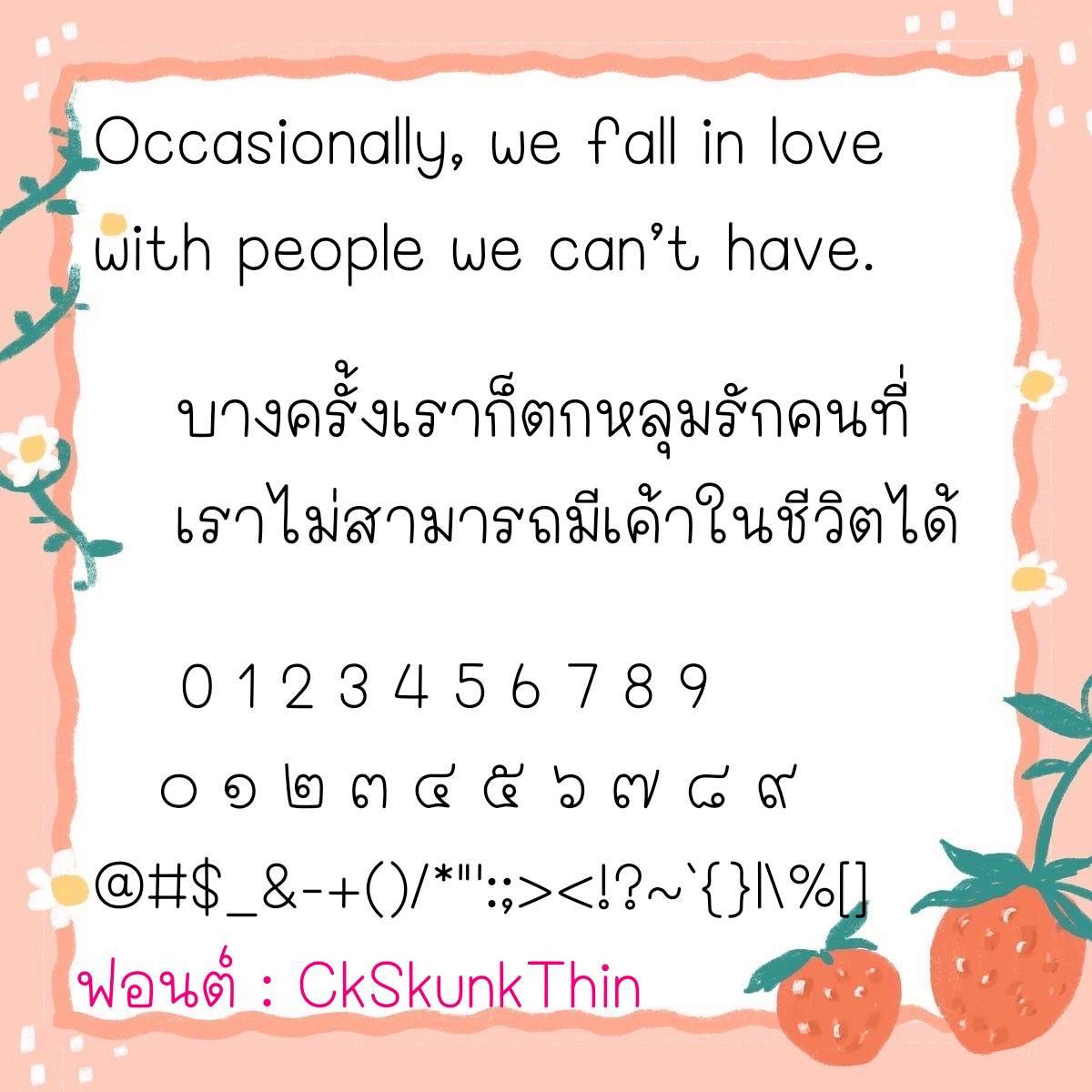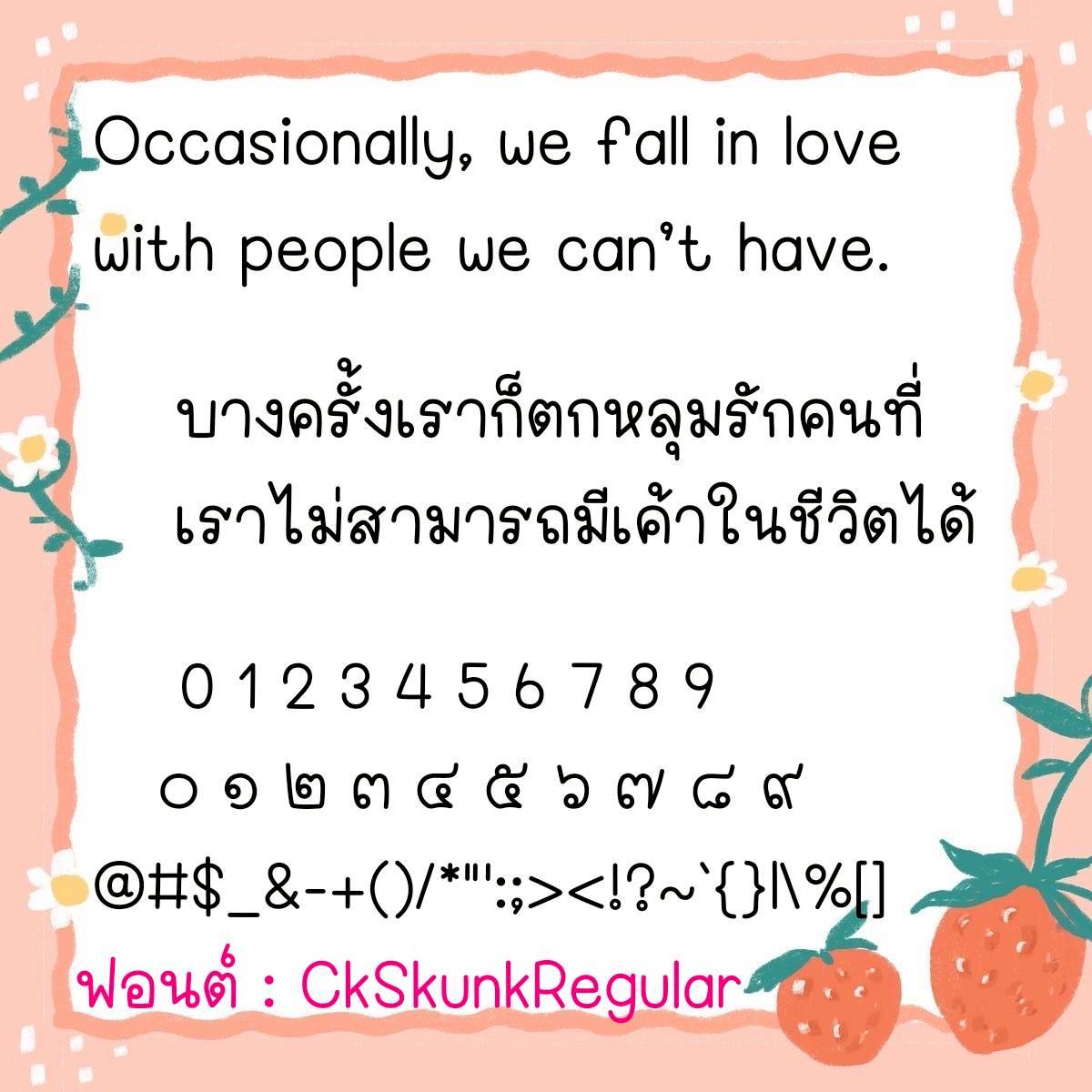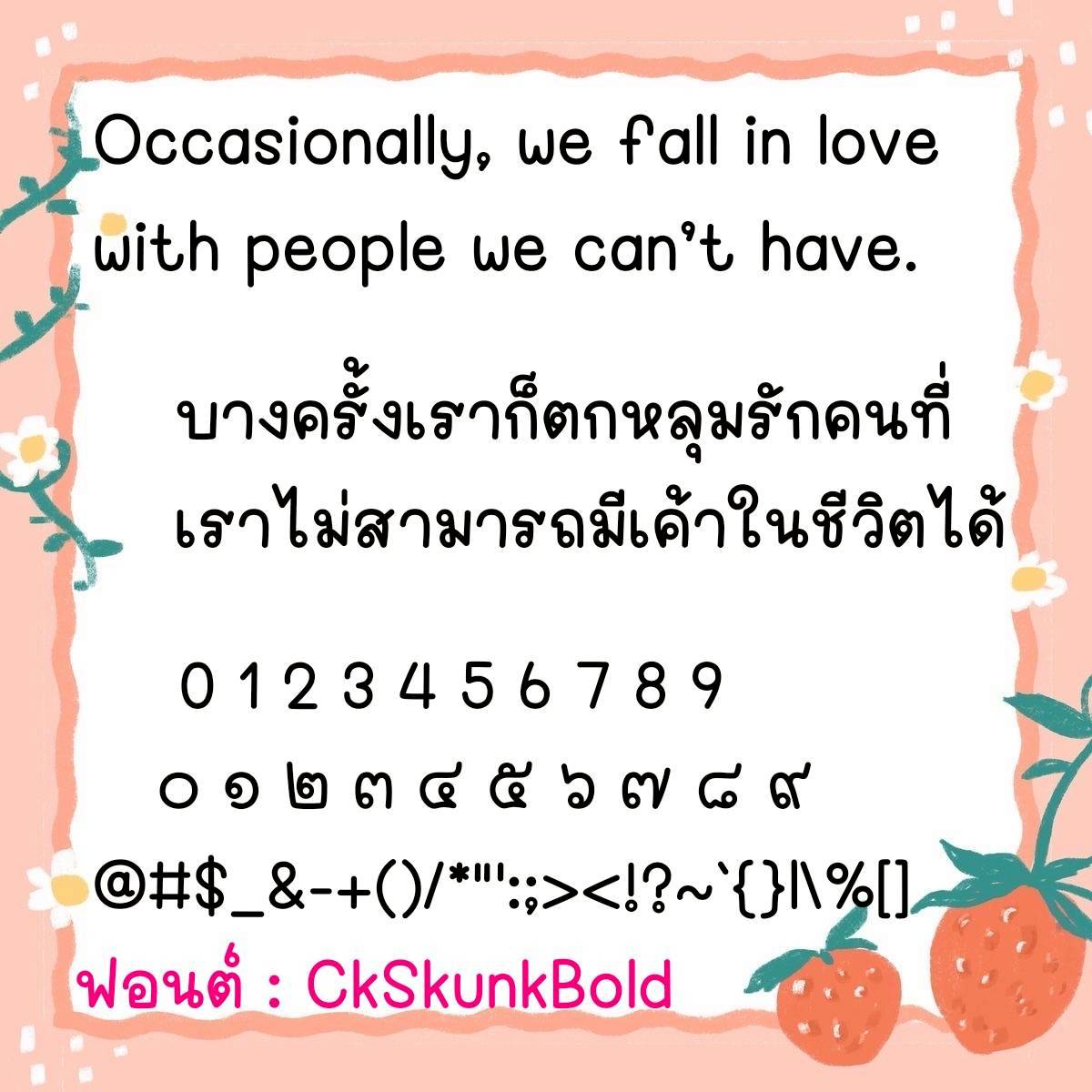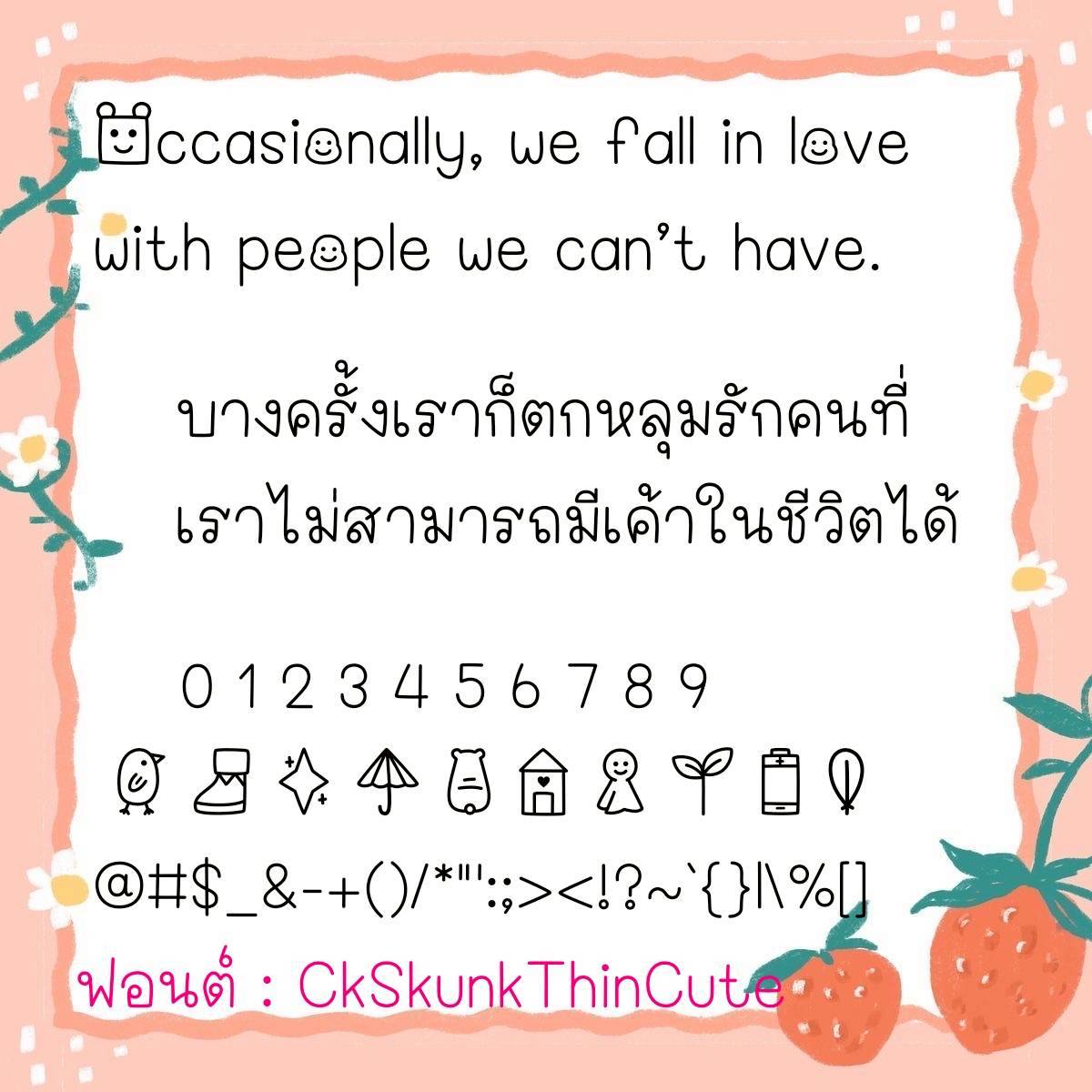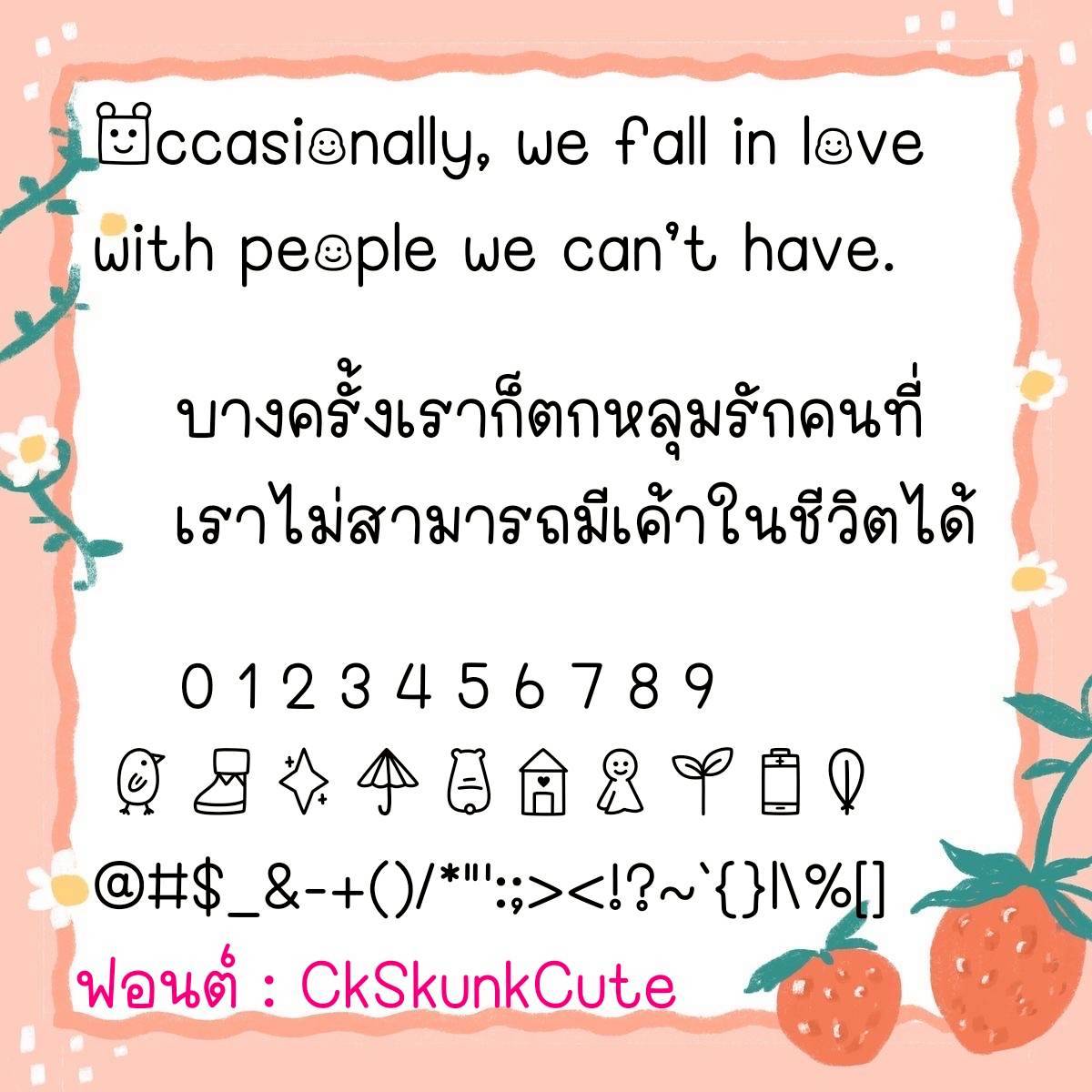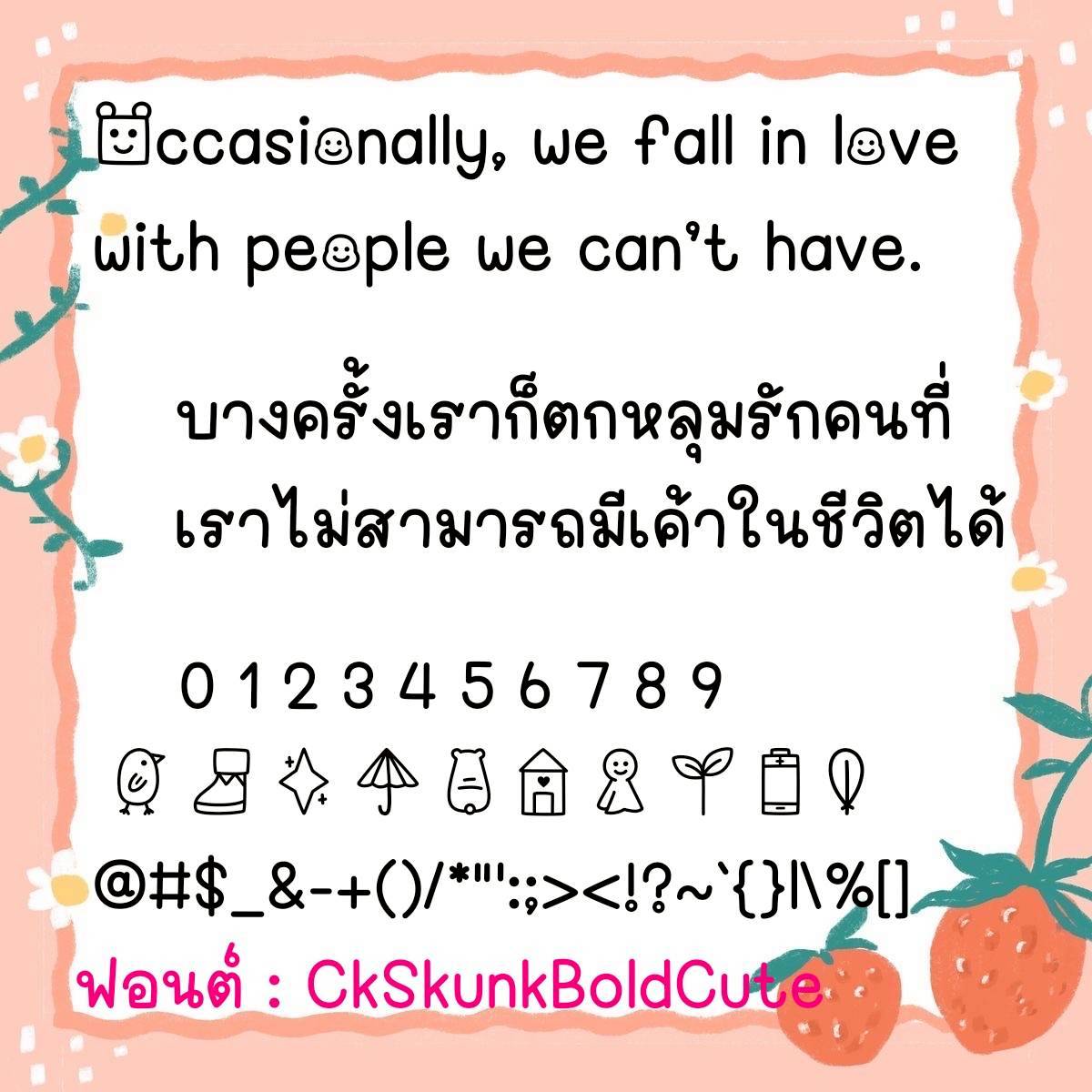
Font CkSkunk
🔸 ฟอนต์ลายมือตัวอวบอ้วนน่ารัก เป็นฟอนต์แนวกึ่งวัยรุ่น ใช้งานได้หลากหลาย ดูไม่น่าเบื่อ เน้นอ่านง่าย และยังมีไฟล์อิโมจิน่ารักๆที่ใช้แทนเลขไทยให้ด้วยค่ะ 🥰💙
🔹 This cute, chubby handwritten font is a semi-youthful style, versatile, and never boring. It emphasizes readability and also includes cute emoji files that can be used to replace Thai numerals. 🥰💙
🔸ฟอนต์ลายมือแนววัยรุ่น มีความยึกยัก น่ารักมีสไตล์ดูมีลูกเล่น ดูไม่น่าเบื่อ และยังมีไฟล์อิโมจิน่ารักๆที่ใช้แทนเลขไทยให้ด้วยค่ะฟอนต์ปรับสระเรียบร้อยไม่ลอย ไม่เหลี่ยม ใช้งานได้กับทุกโปรแกรม ได้ทั้ง ios(รองรับกับแอพต่างๆที่รองรับฟอนต์ในios เช่น Goodnote, Procreate)/android/คอมฯ/Ps/Word,Excel ได้หมดจ้าาาาา❤️❤️❤️